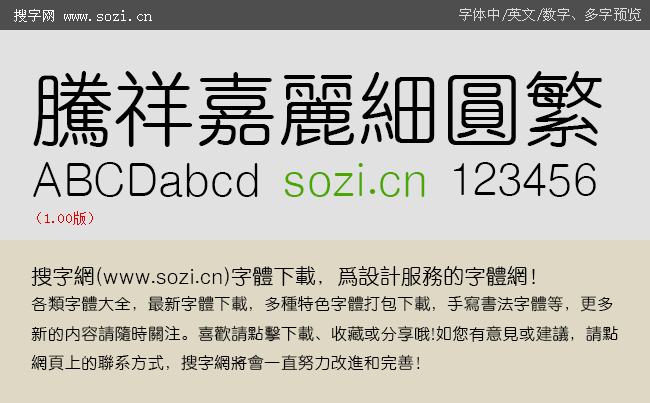
騰祥嘉麗細(xì)圓繁
搜字網(wǎng)提供一款騰祥嘉麗細(xì)圓繁字體下載,該字體每個(gè)漢字都經(jīng)過精心設(shè)計(jì),筆畫粗細(xì)均勻、結(jié)構(gòu)美觀。每個(gè)字的圓角、圓頭、勾形都極光潔、風(fēng)格統(tǒng)一,字形放大不變形,縮小顯示清晰,適用于樣本畫冊(cè),報(bào)紙排版,網(wǎng)頁(yè)標(biāo)題等廣告設(shè)計(jì)應(yīng)用。